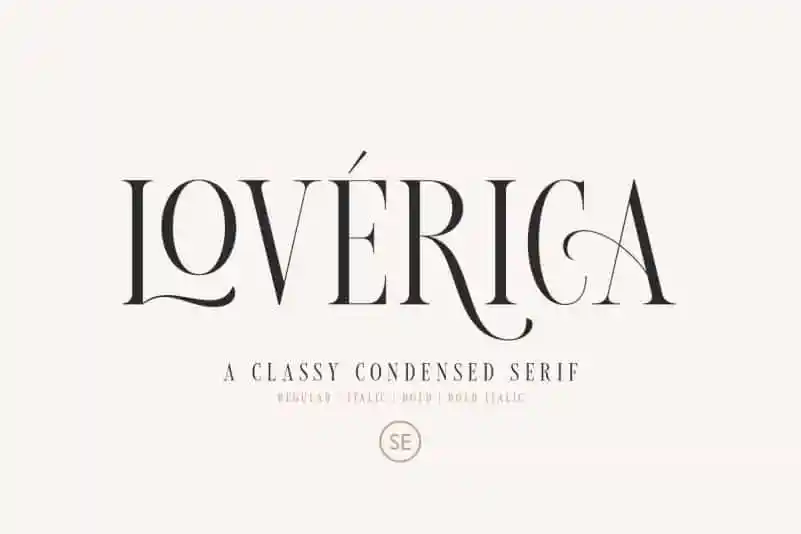
Loverica Serif Font – Download Grátis
A Loversica Serif Font é uma tipografia com caracteres elegantes que oferece muitas alternativas ao longo de sete estilos para cada letra. Ideal para trabalhos elegantes e vintage, essa font foi criada pelo designer Sarid Ezra através do site 99designs. Ela combina características clássicas e modernas, garantindo um design inovador que tornará seus documentos ou logomarcas ainda mais impressionantes e distintivos. Esta font está pronta para atender a múltiplos idiomas e já inclui PUA (Personal Use Attribute) encoding, o que significa que você pode usá-la sem preocupações legais. Seu design sofisticado combina elegância com modernidade, permitindo-lhe usar em muitos propósitos diferentes. Seja para gráficos de marca, cartões de visita, editoriais ou qualquer outro tipo de material, Loversica Serif é uma escolha excelente para quem deseja dar um toque especial e único ao seu trabalho.